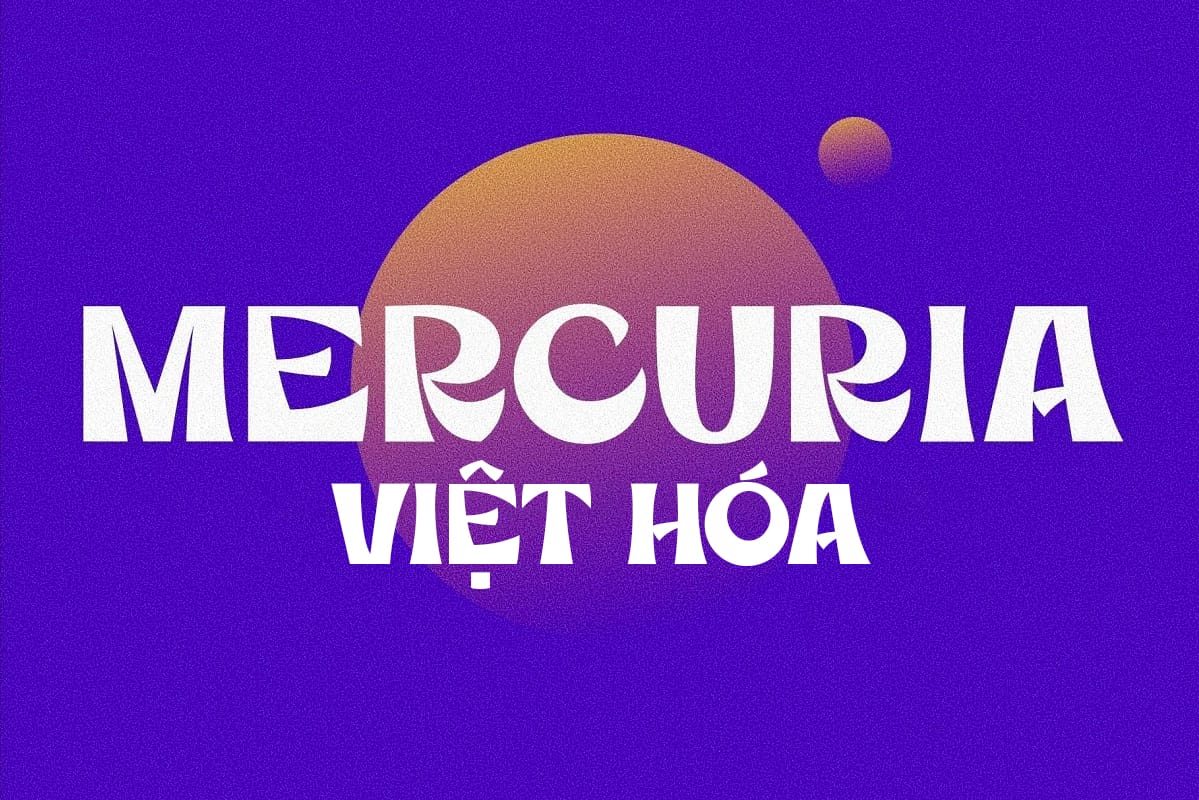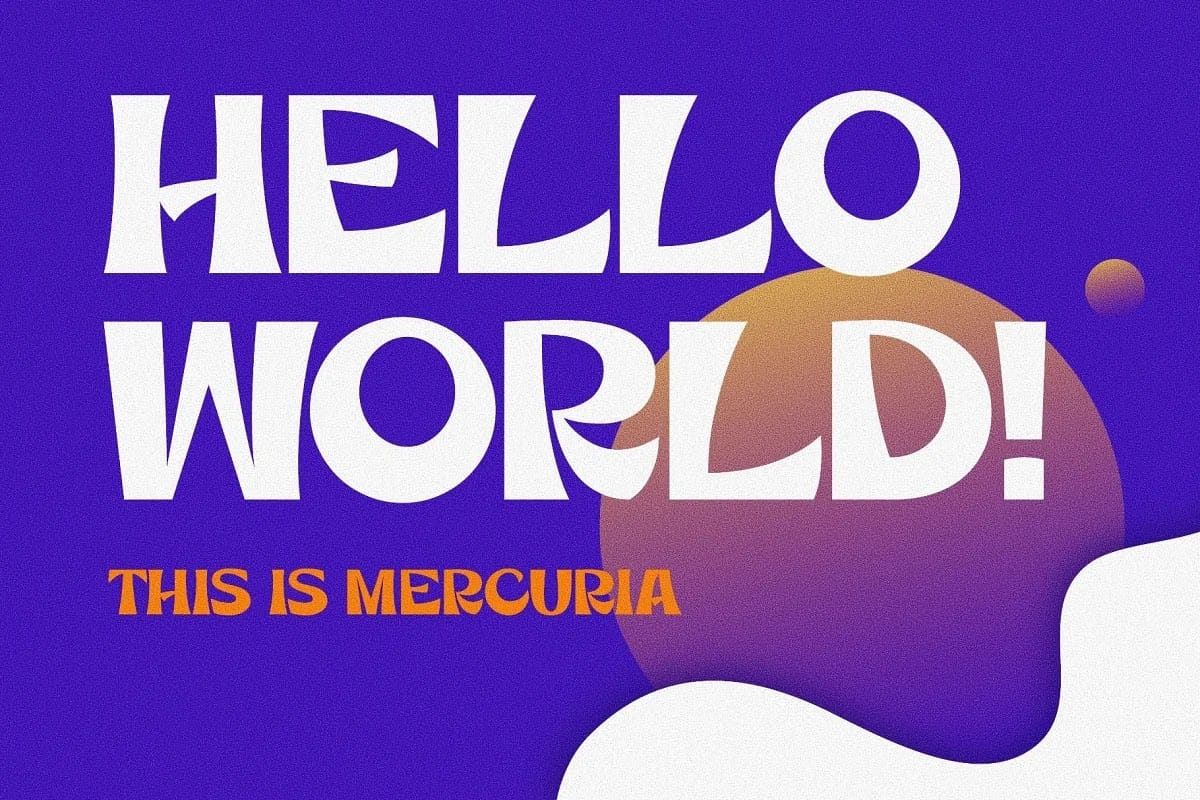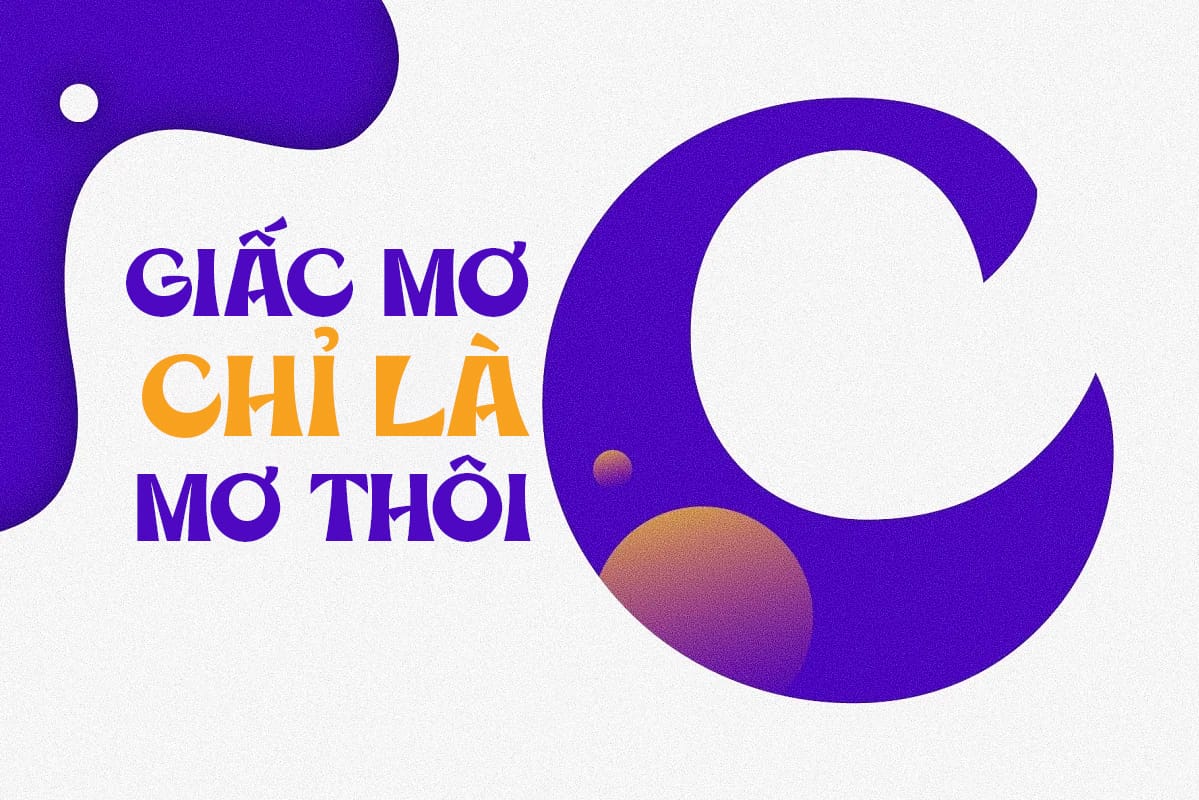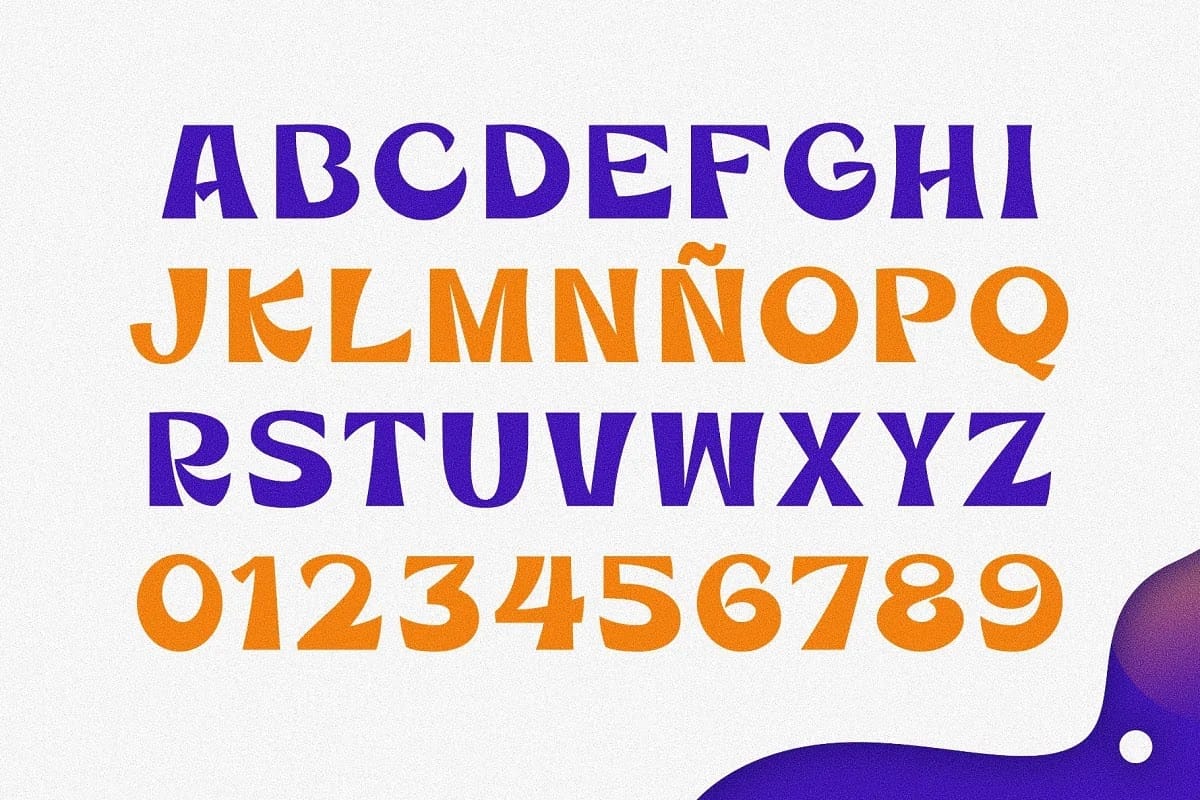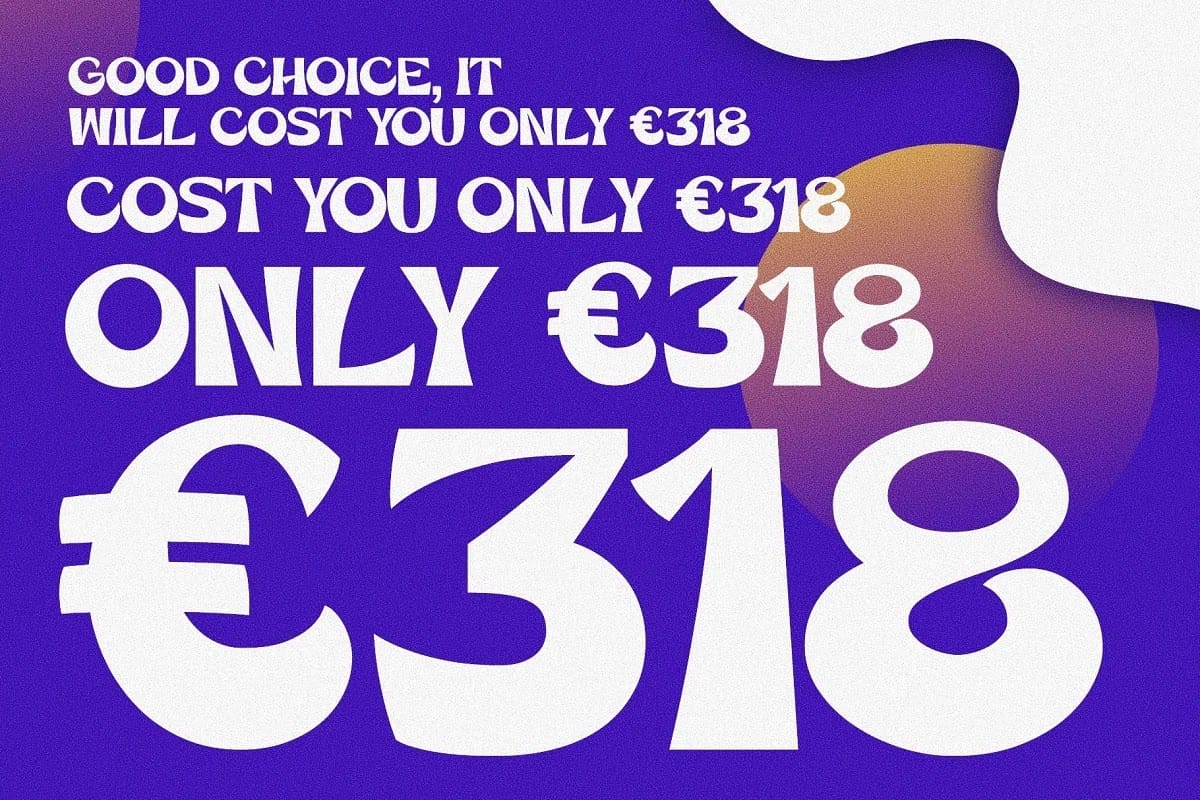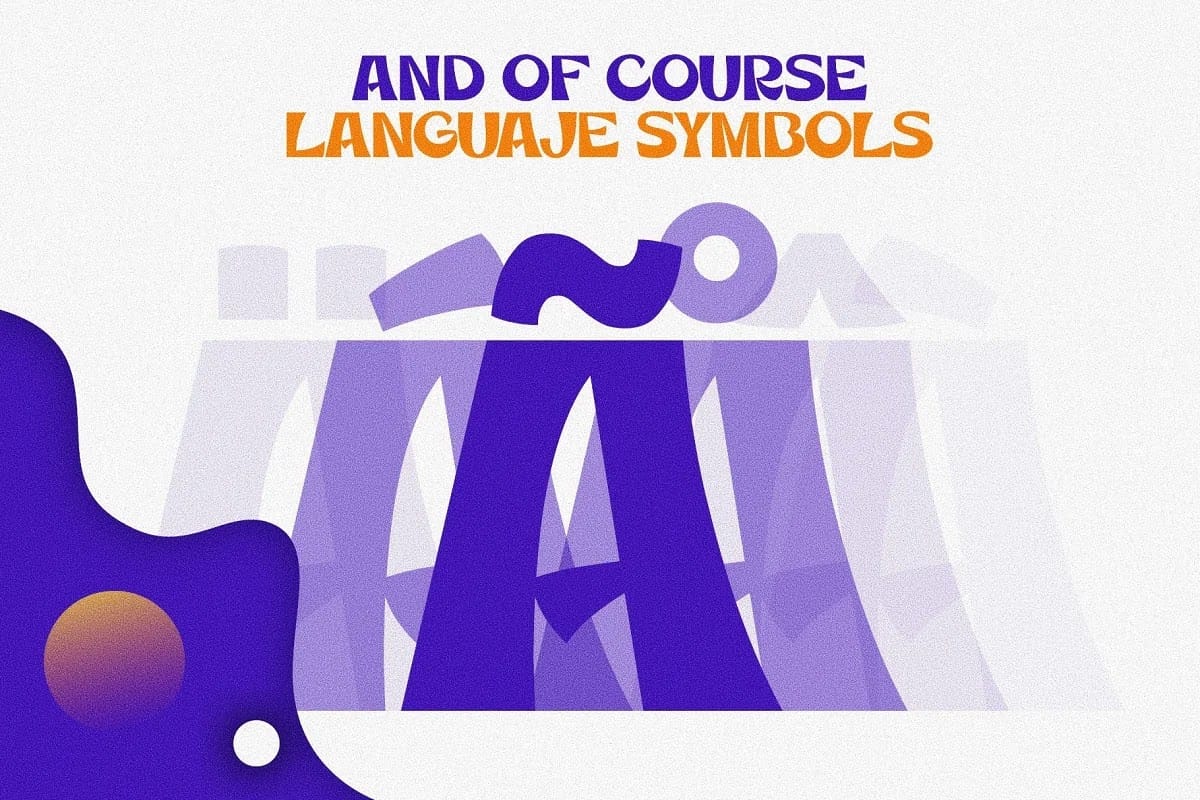
Font Mercuria Việt Hóa – Font chữ đậm, mạnh mẽ
Font MERCURIA Việt Hóa, một font chữ đậm, mạnh mẽ và thân thiện.
Phong cách độc đáo của nó cho phép Mercuria được sử dụng trong nhiều không gian và dịp khác nhau, dù chỉ sử dụng một chữ cái hoặc tạo ra các dòng văn bản dài, nó sẽ hoàn toàn phù hợp, mang đến cho thiết kế của bạn nét hoàn hảo và cần thiết về sự độc đáo và phong cách.
Đặc trưng:
Hơn 240 ký tự, chứa:
• Chữ hoa
• Chữ số
• Các ký hiệu dấu câu, số và các ký tự đặc biệt khác
• Ký tự đa ngôn ngữ